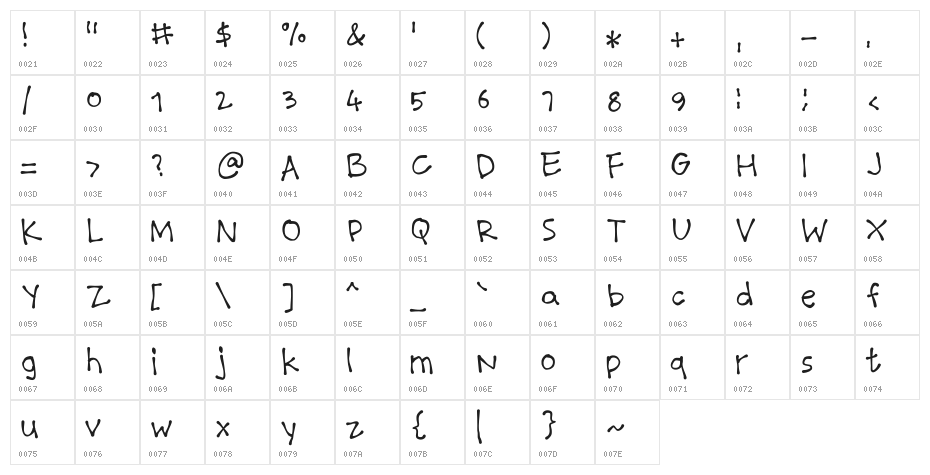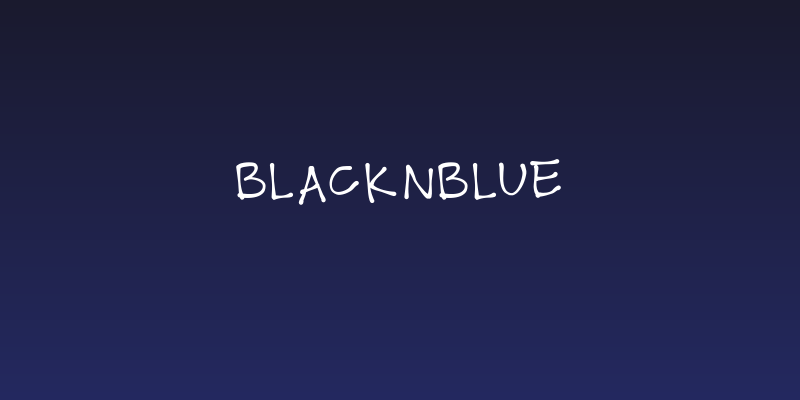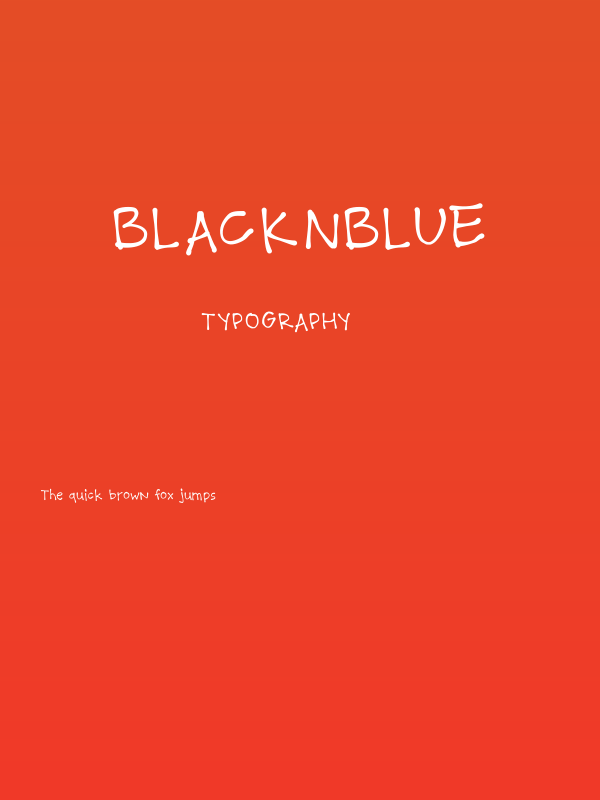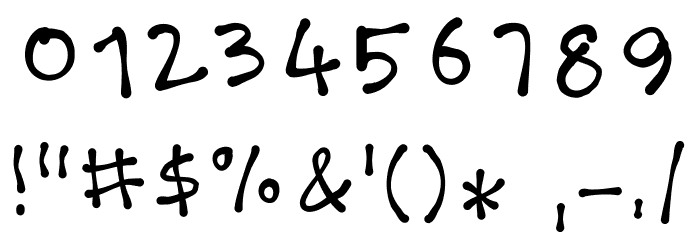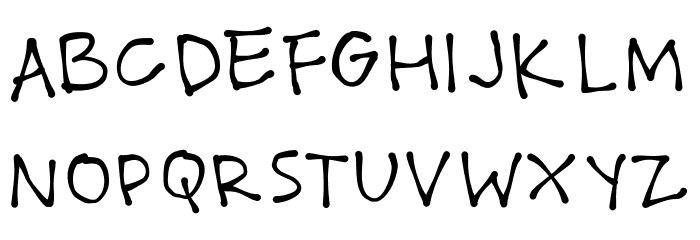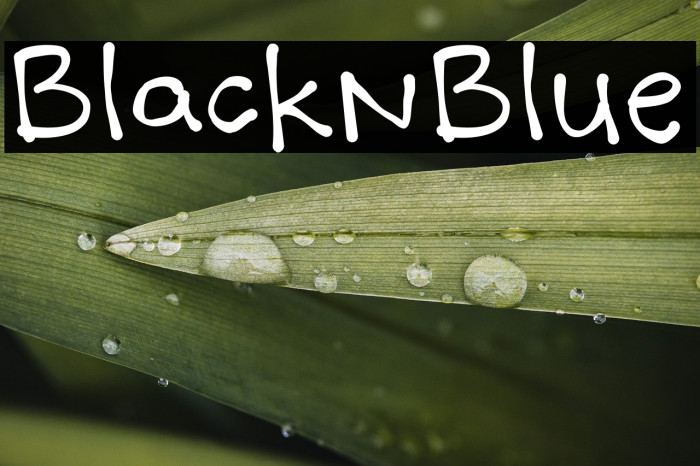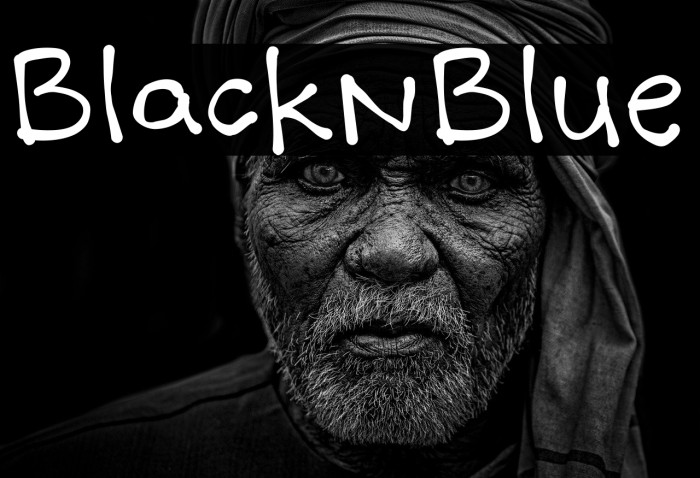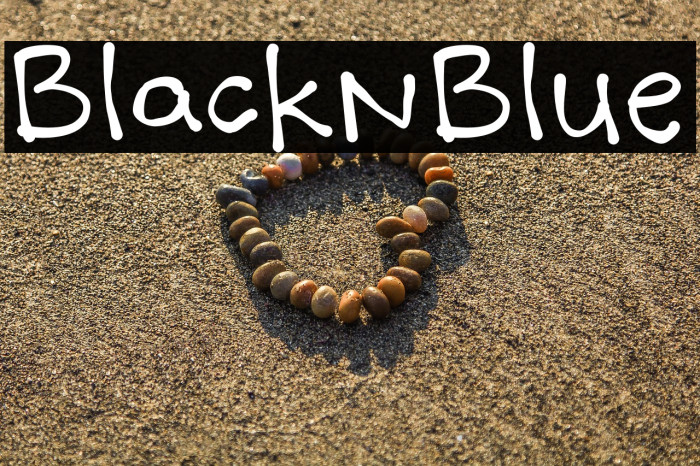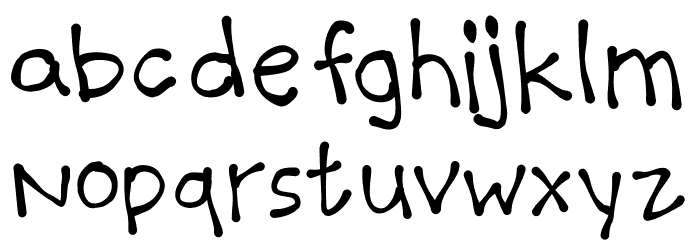
BlacknBlue Font
| Gesamtstil | Casual |
| Anwendungsfall | Headlines, Informal text, Creative projects |
| Vorgeschlagene Projekte | Ideal for children's books, greeting cards, informal invitations, and playful branding projects. |